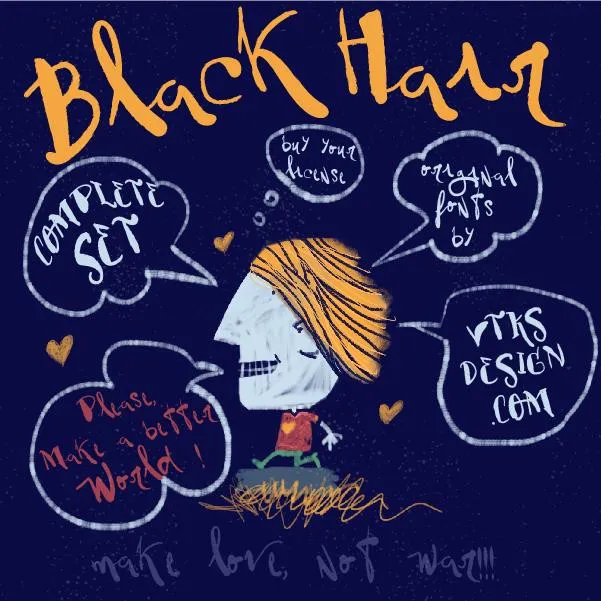
Vtks BlackHair font – Download Grátis
A ‘Vtks BlackHair’ é uma fonte que adiciona um toque único aos seus projetos digitais. Inspirada no cabelo preto luxuoso, essa elegante e sofisticada tipografia se destaca na categoria de Fonts Playful. Desenvolvida pelo designer Hamilton, ela tem um charme peculiar capaz de dar vida a qualquer projeto, seja em logotipos, design gráfico ou até mesmo artesanato digital. Com um estilo irresistivelmente sedutor e um ar de sofisticação, ‘Vtks BlackHair’ oferece uma maneira divertida de personalizar seu material visual. Seja você um designer de jogos, webmaster ou criador de redes sociais, acredite que essa fonte é perfeita para destacar seus trabalhos. Se quiser adquirir a licença dessa maravilhosa fonte em dólares, simplesmente siga o link fornecido na descrição original. Compreender e aplicar a ‘Vtks BlackHair’ no seu próximo projeto pode ser um processo agradável e divertido. Quebre as regras do design com esta fonte única e permita que ela seja o ponto final para seus trabalhos, criando uma imagem memorável em cada página ou arquivo digital. Para adquirir sua licença da font, basta clicar no link fornecido na descrição original.